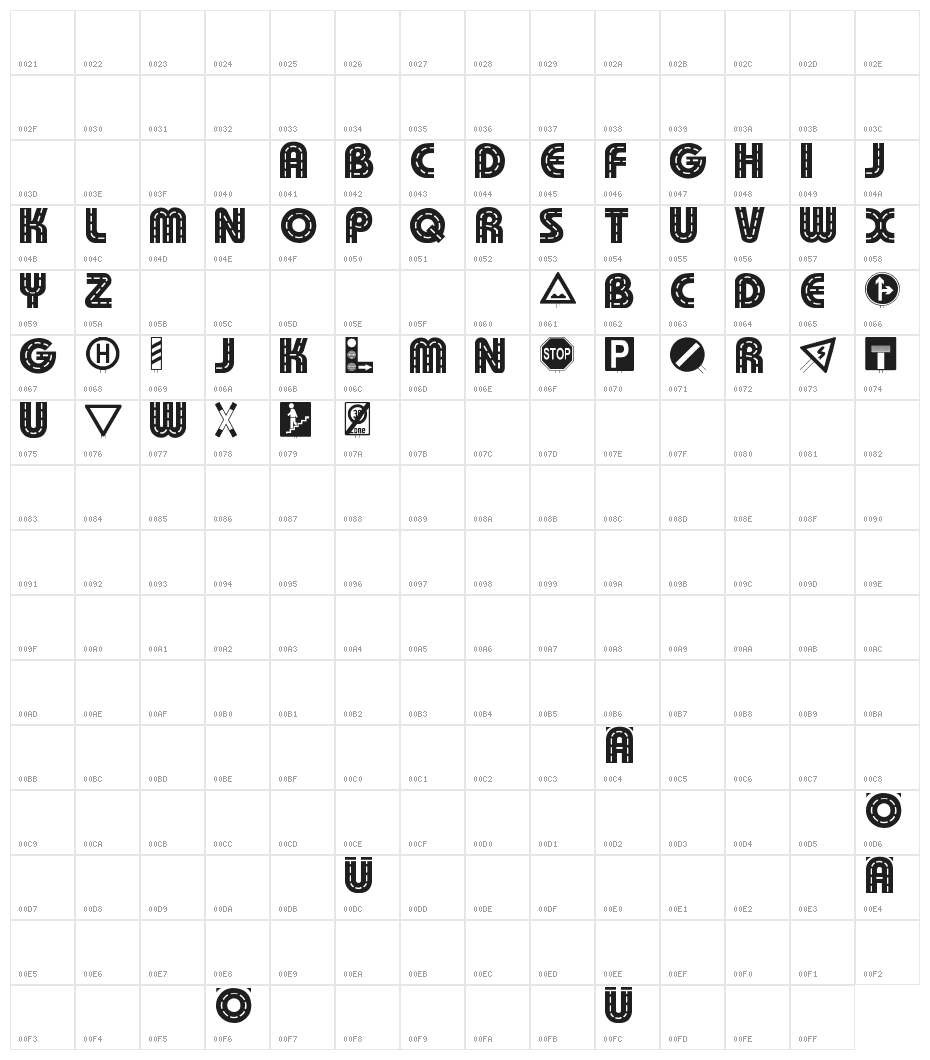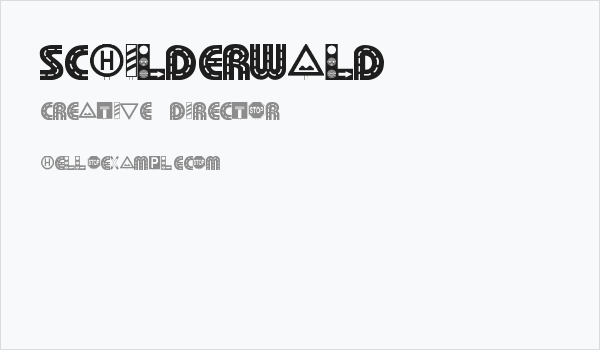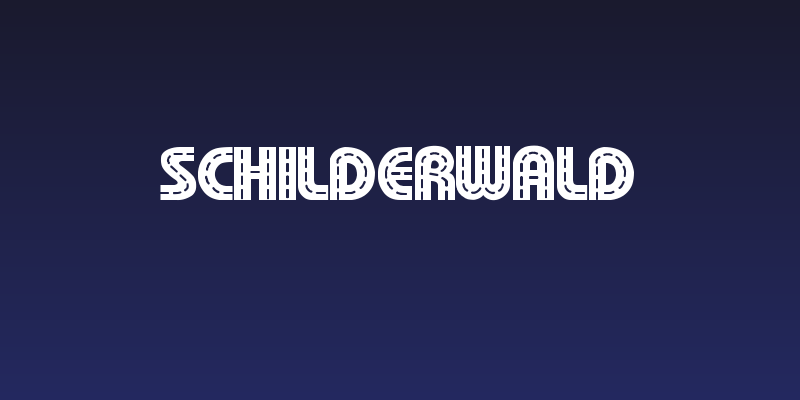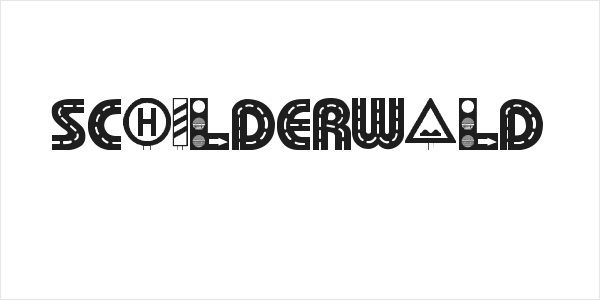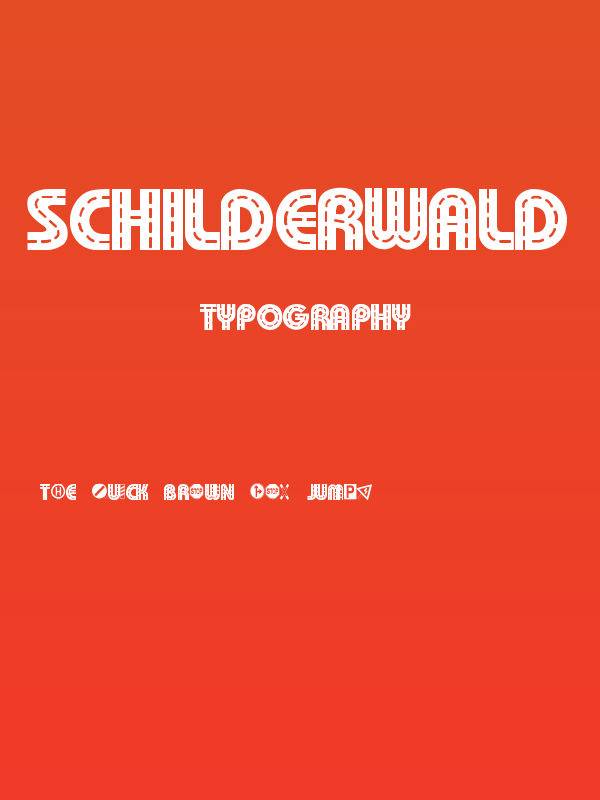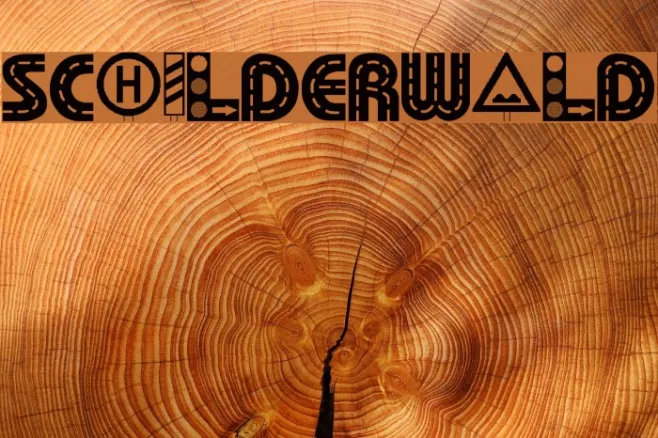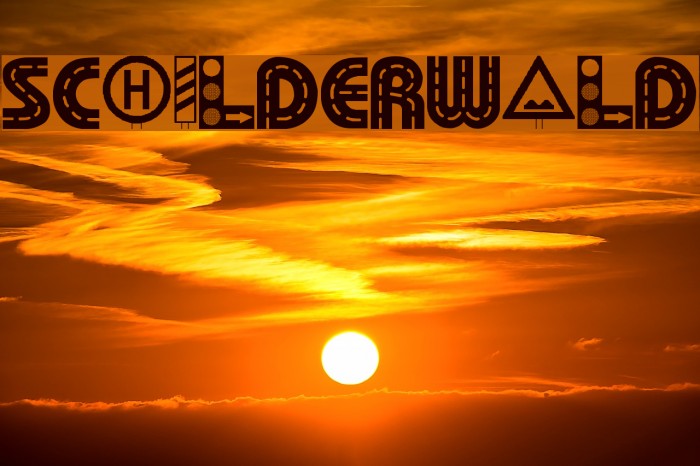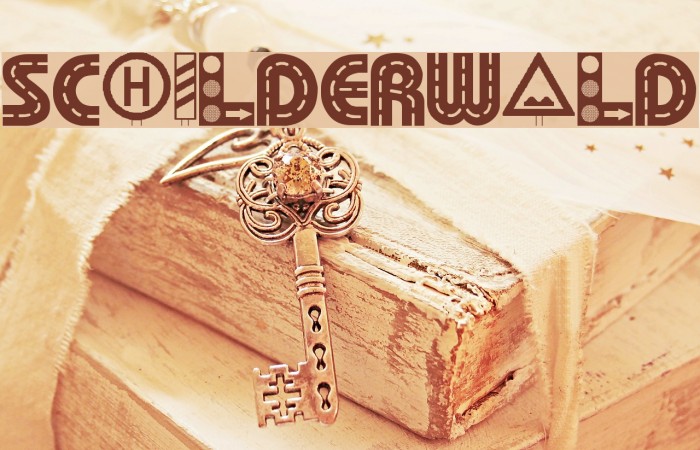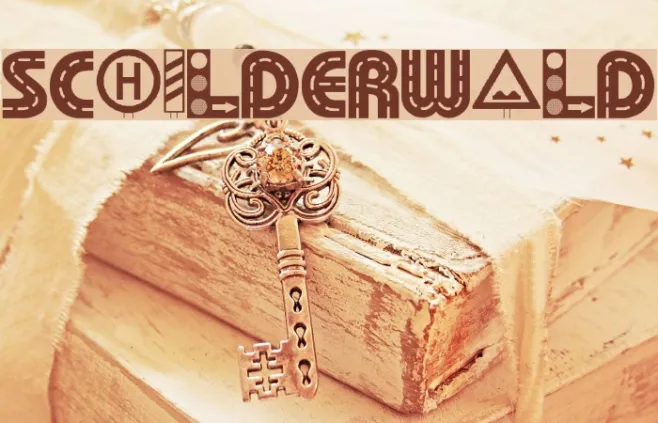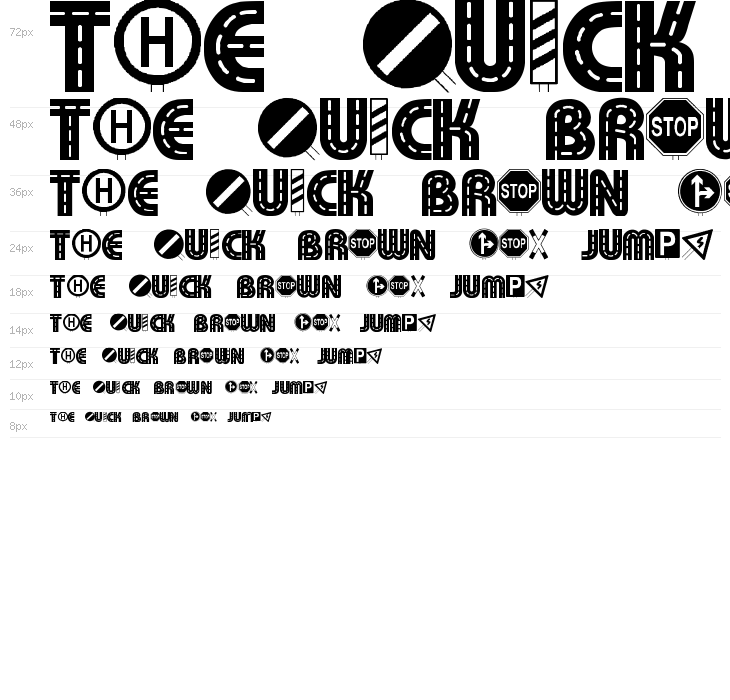
Schilderwald Font
| Progetti proposti | Ideal for creative projects such as posters, themed event invitations, educational materials about road safety, and any design requiring a playful, thematic touch. |